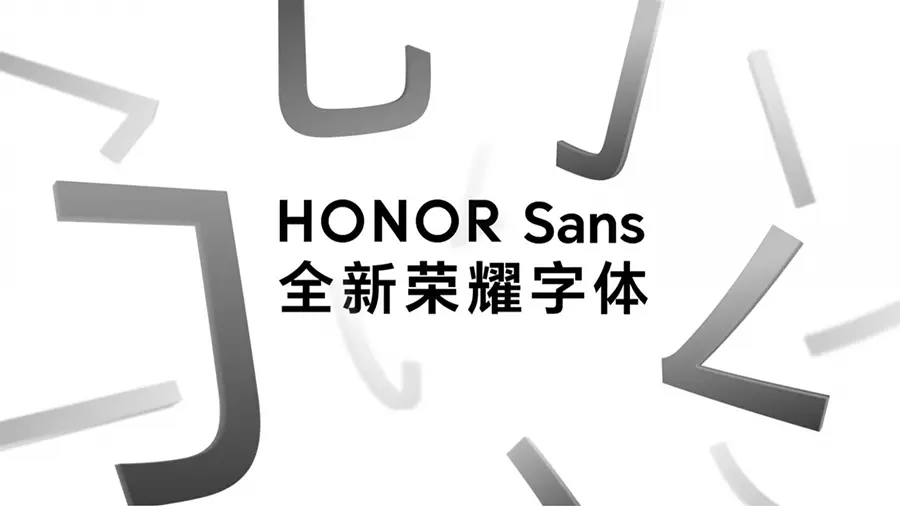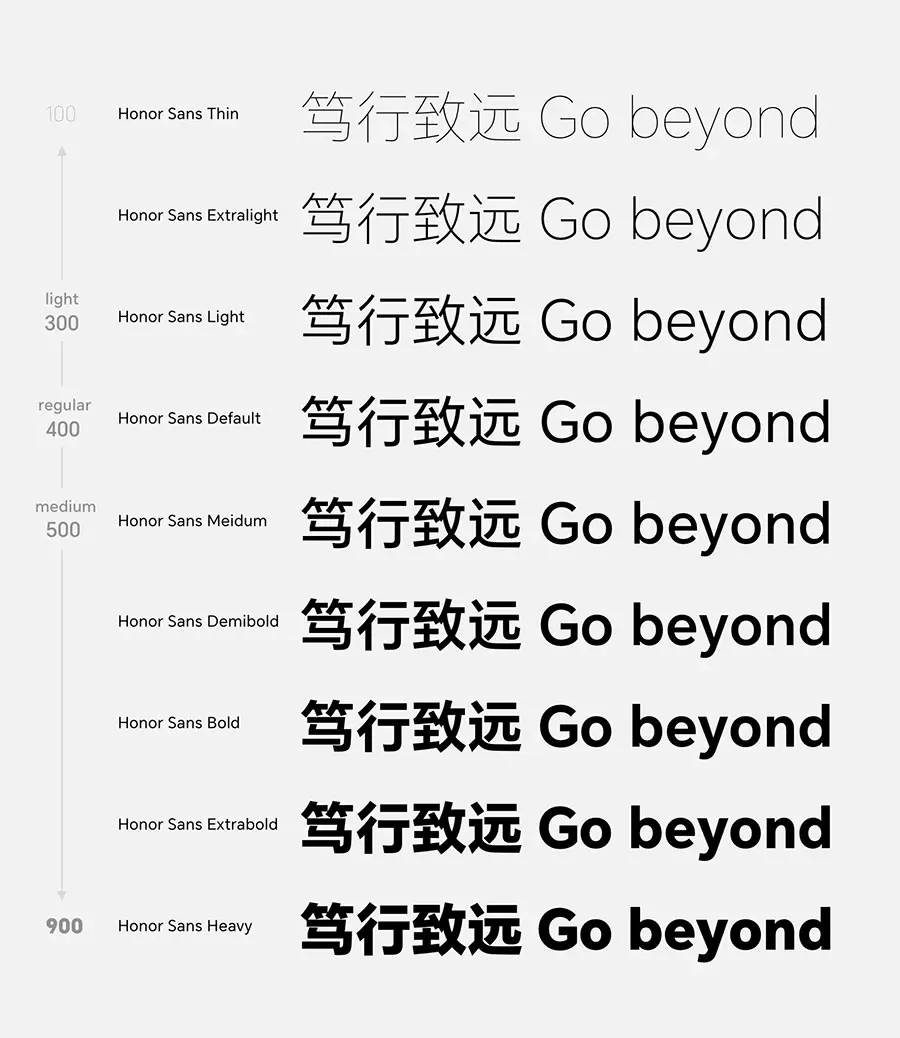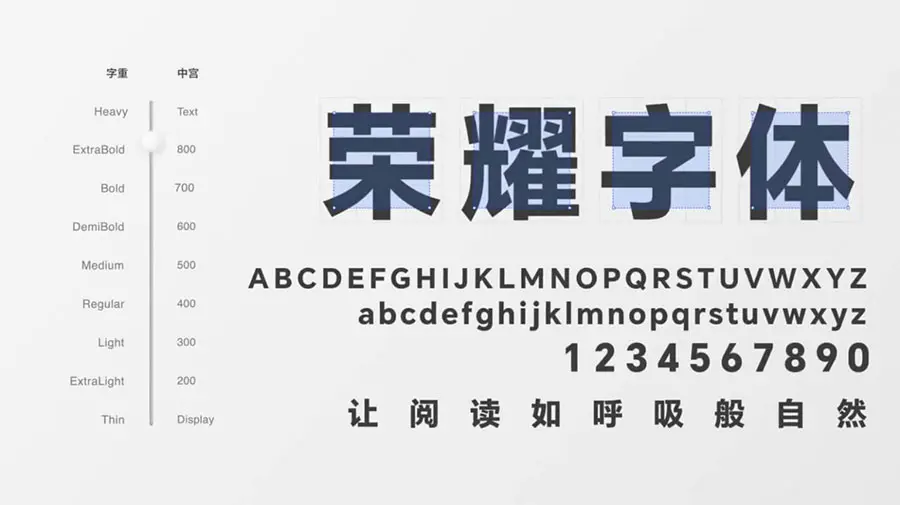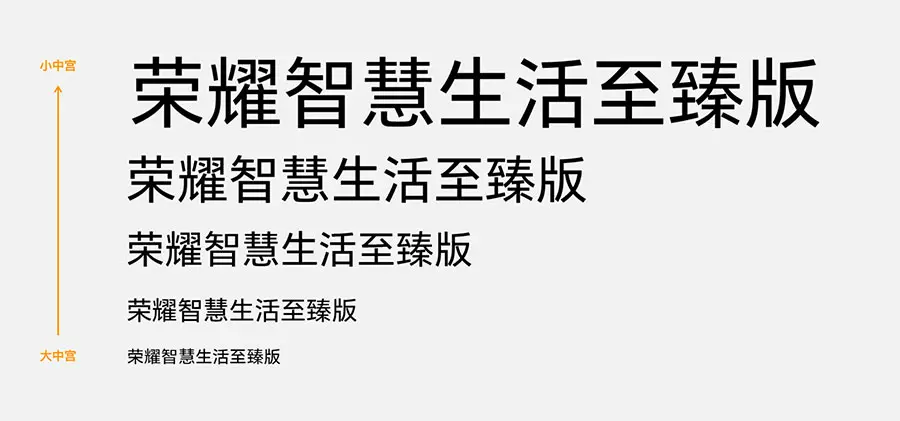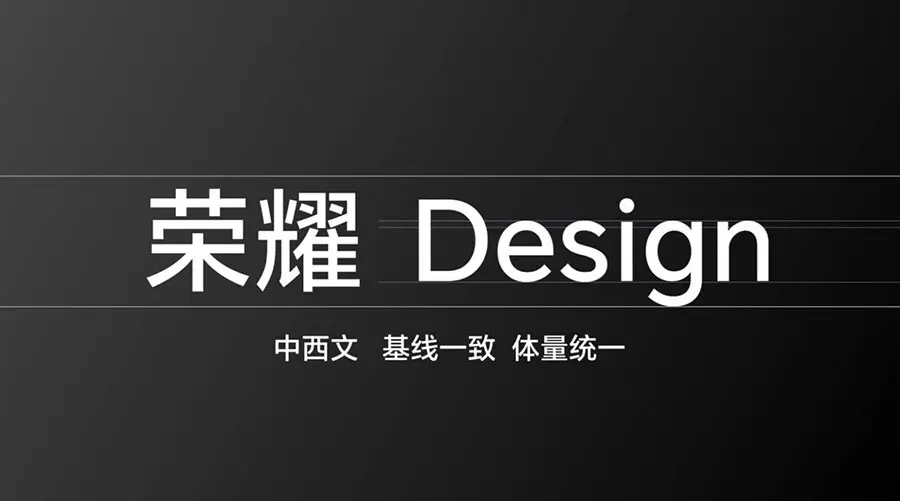
在榮耀 MagicOS 7.0 發佈會上,榮耀還帶來了全新的榮耀字體(HONOR Sans) 字體,號稱是業界首款支持字重和中宮雙重無極可變的字體,將榮耀字體與 UI 融合,通過間距優化,讓排版更整齊,層次更清晰。
榮耀將其稱為”會呼吸的字體“。HONOR Sans 將面向全社會免費授權開放,覆蓋全場景全人群使用,而且未來也將推送到榮耀全場景設備上。這款 HONOR Sans 字體現已正式上架開發者網站,面向社會免費提供下載。
HONOR Sans以黑體為基礎,為創作者帶來了一種新的黑體選擇,在海報、視頻字幕、說明文字等方面都能充分起到作用。
Honor sans增加了Thin、Extralight、Light、Default、Medium、Demibold、Bold、Extrabold、Heavy的字重能力,滿足不同人群的對字體對比度的需求,滿足不同領域字體一致的清晰度,可以選擇需要的字重來構建界面的信息層級。
HONOR Sans 以黑體為基礎,能夠根據用戶需求對字重和中宮進行調節,從而在不同環境下均能確保字體的勻稱美觀。在設計上,HONOR Sans 相比標準的黑體則在筆畫曲率、結構佈局上進行了優化,在不影響字體可讀性的前提下,有效提升了字體的舒適性,降低了長時間閱讀時對視覺造成的疲勞。